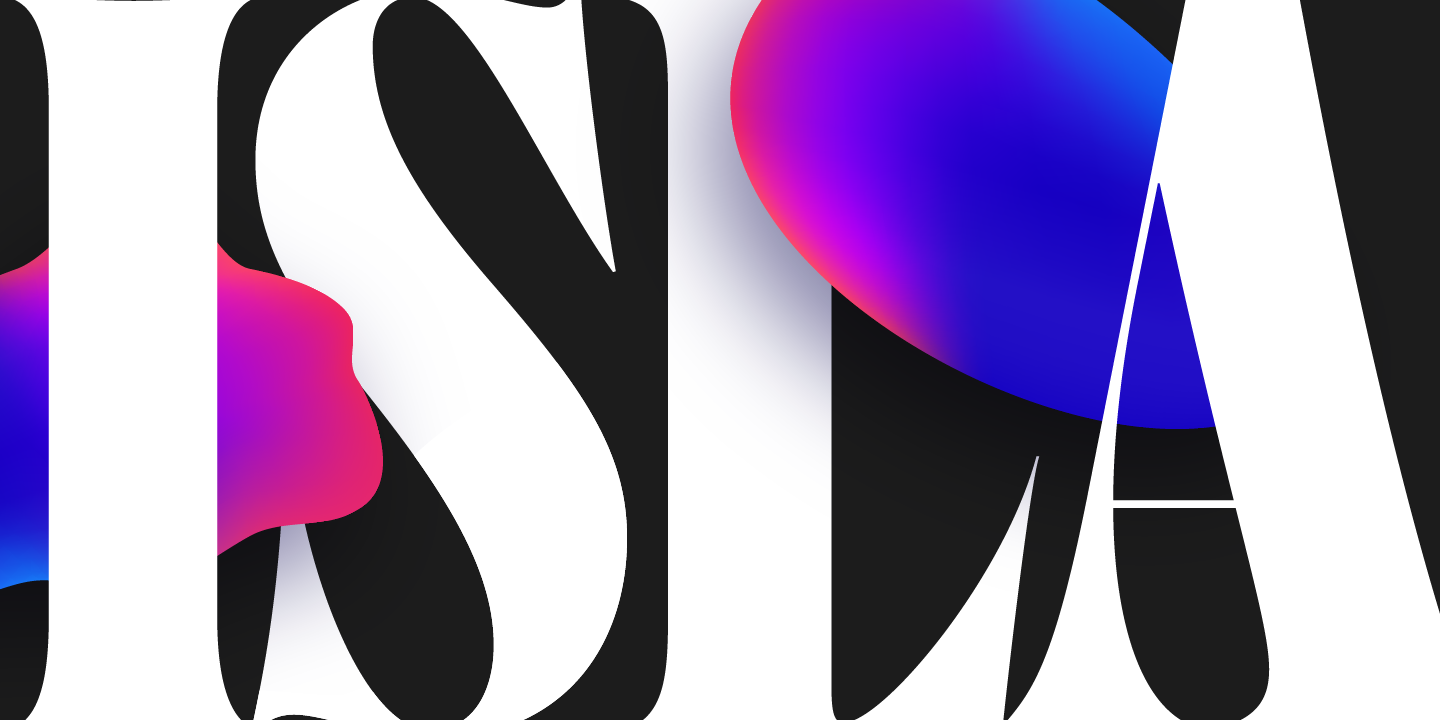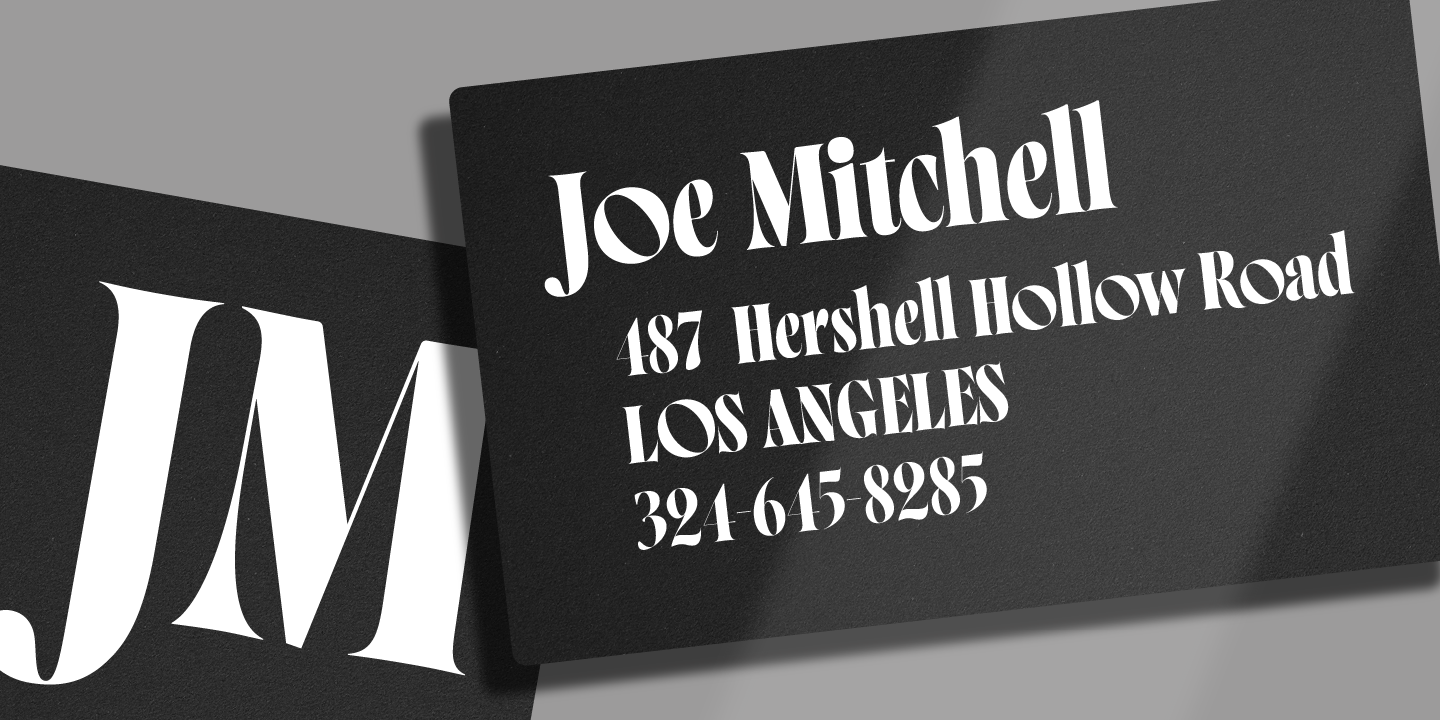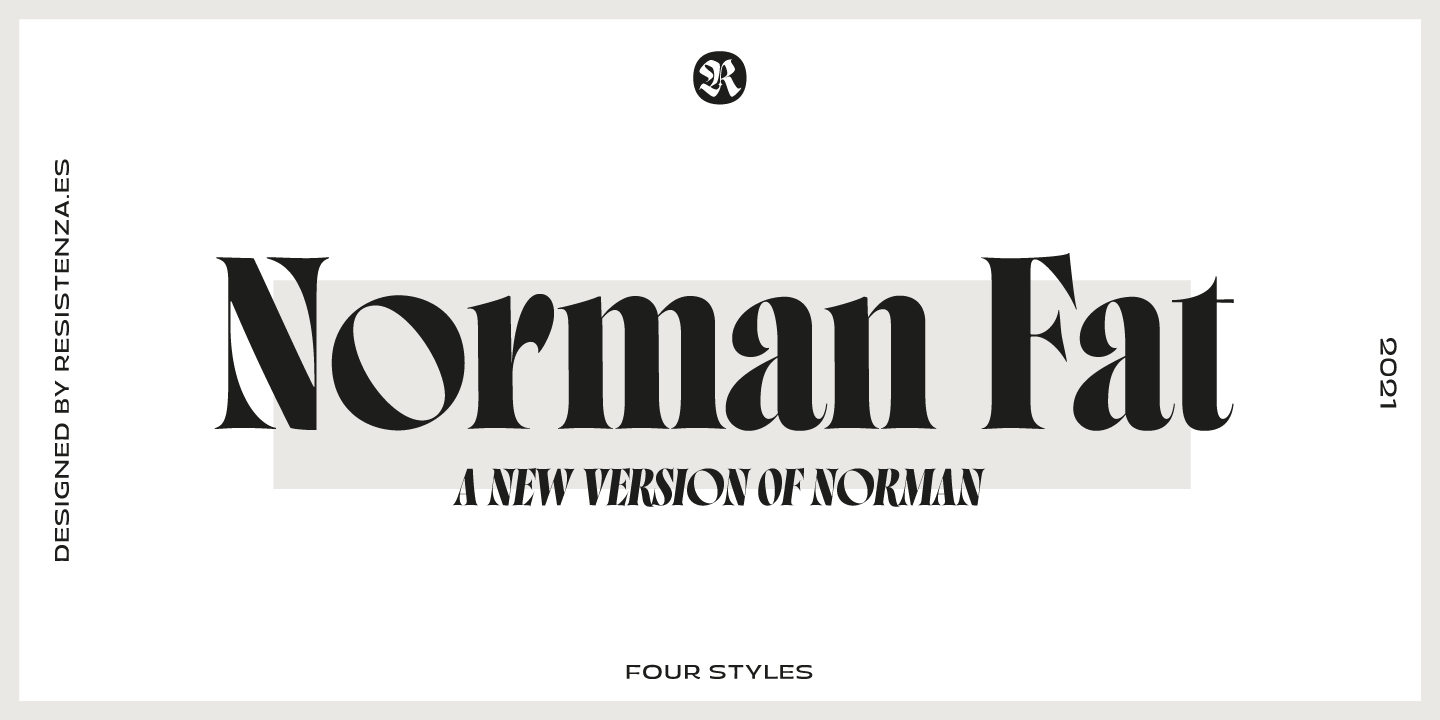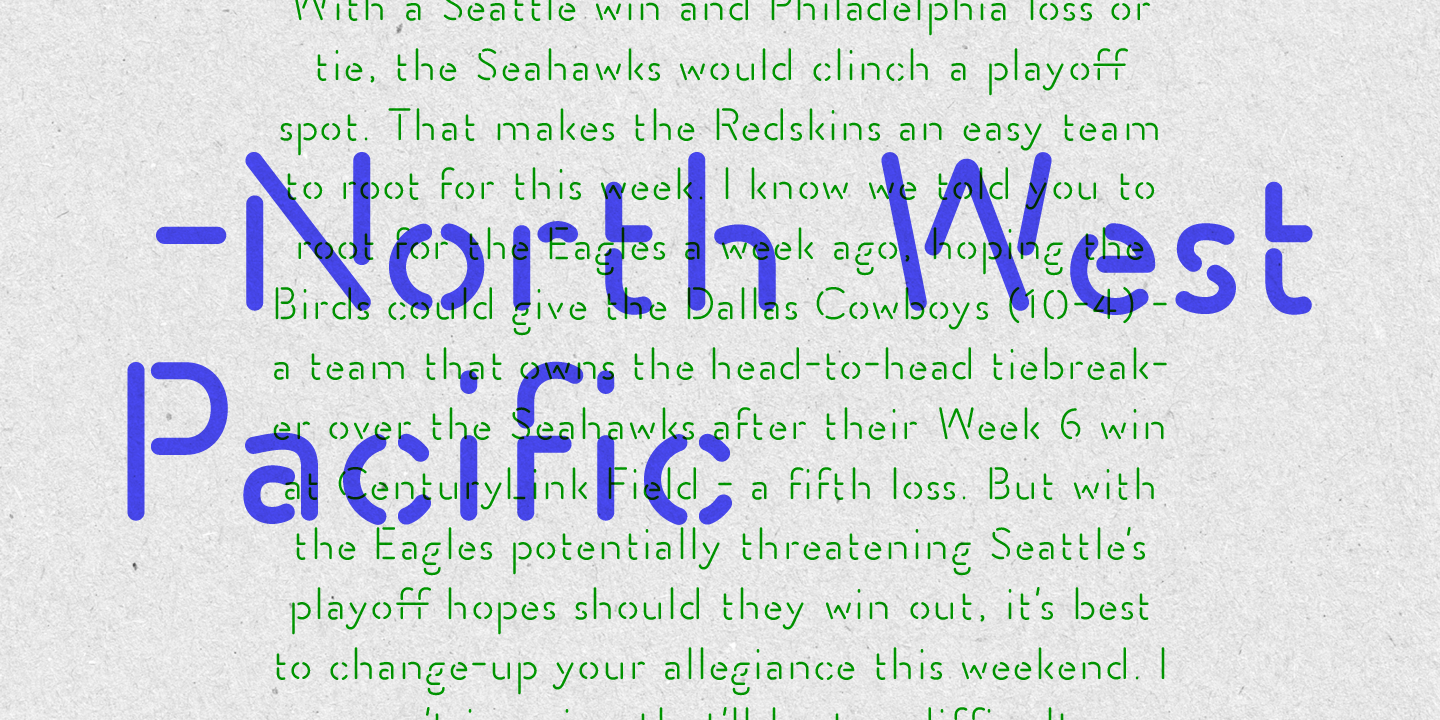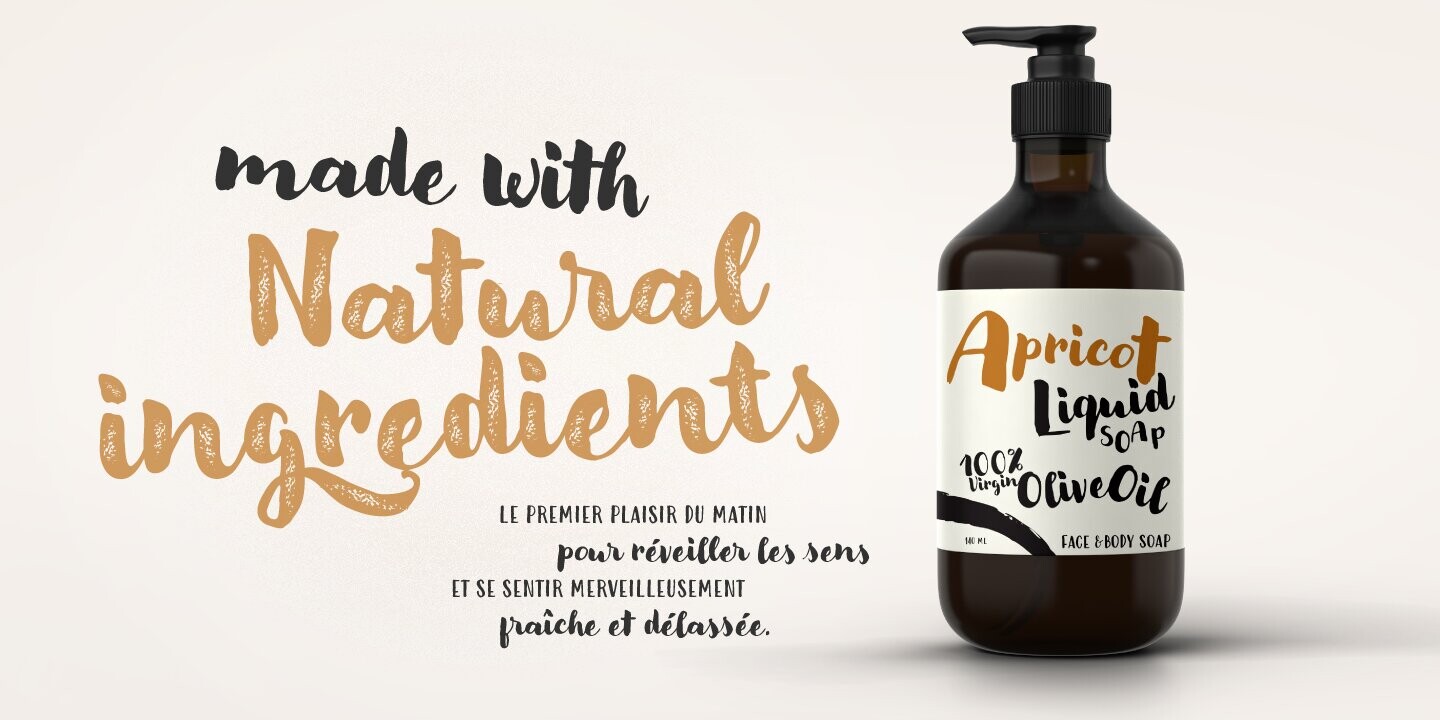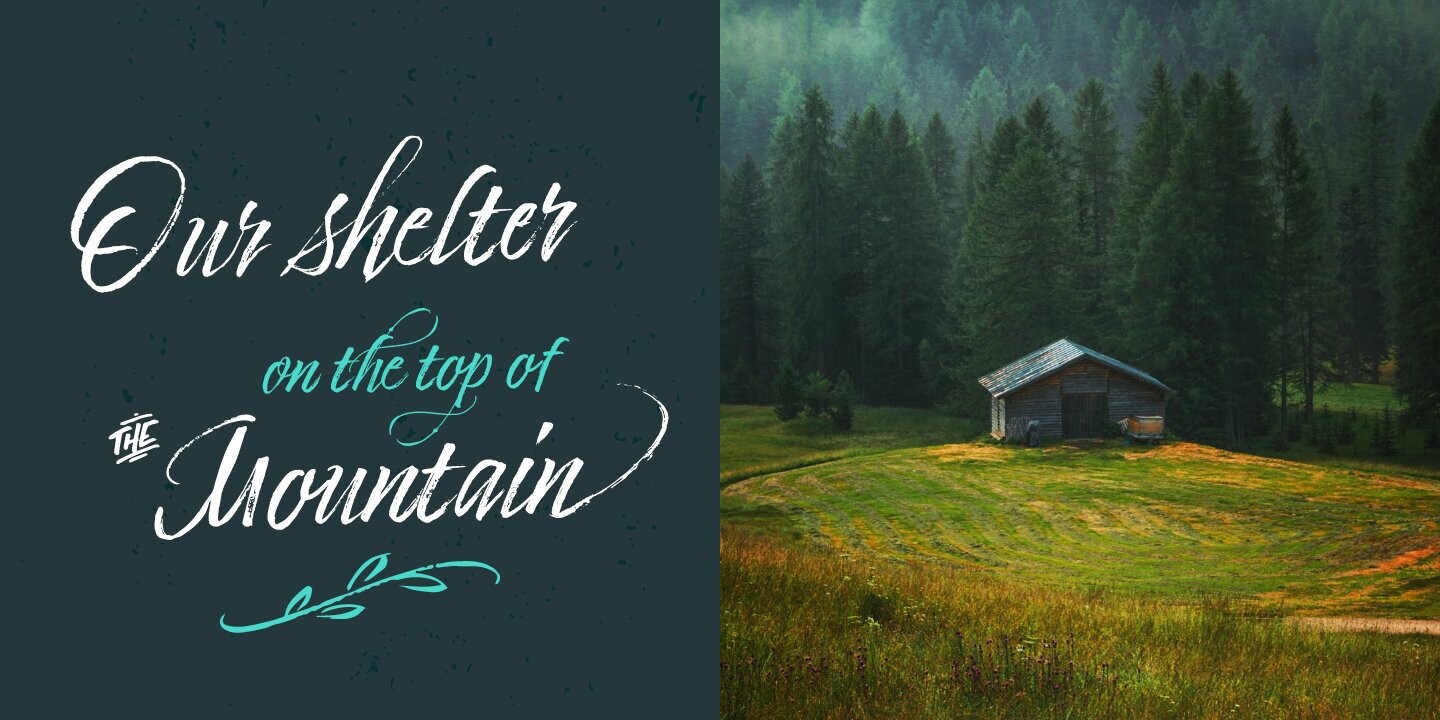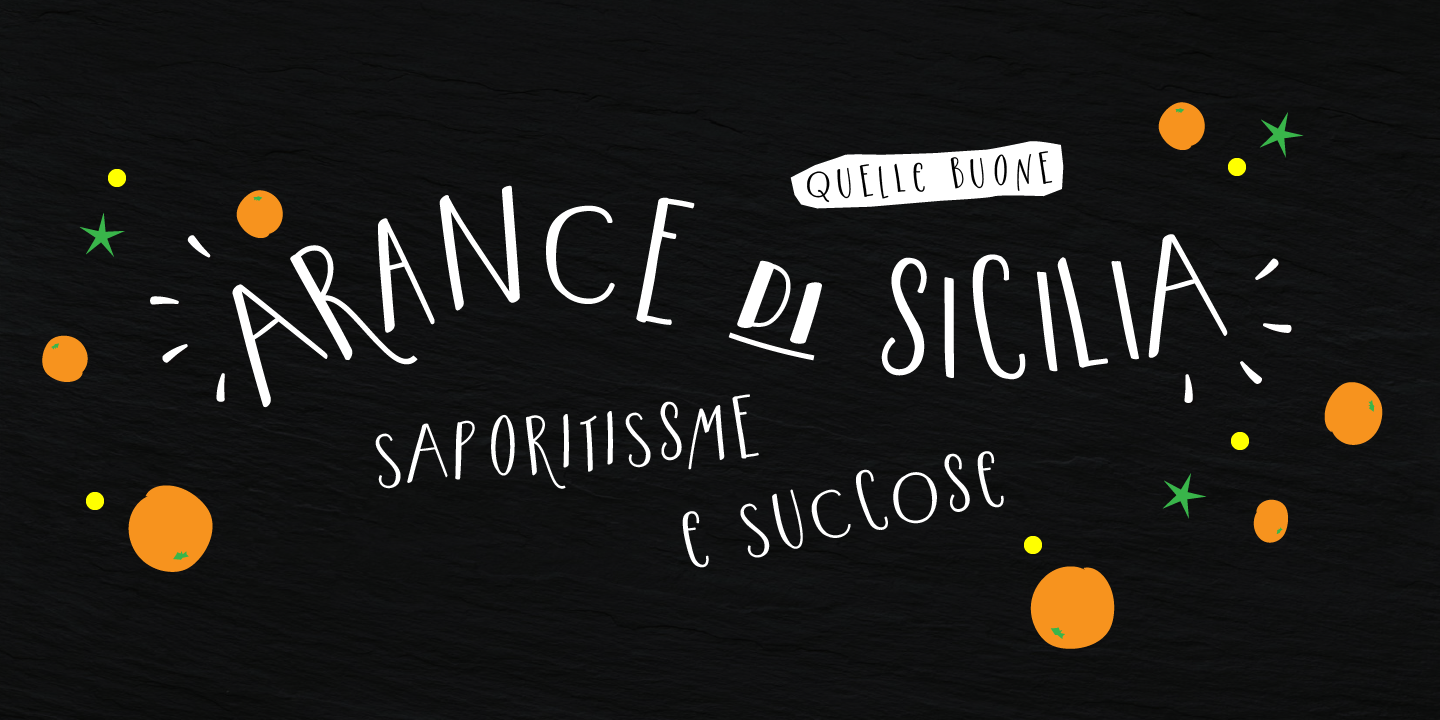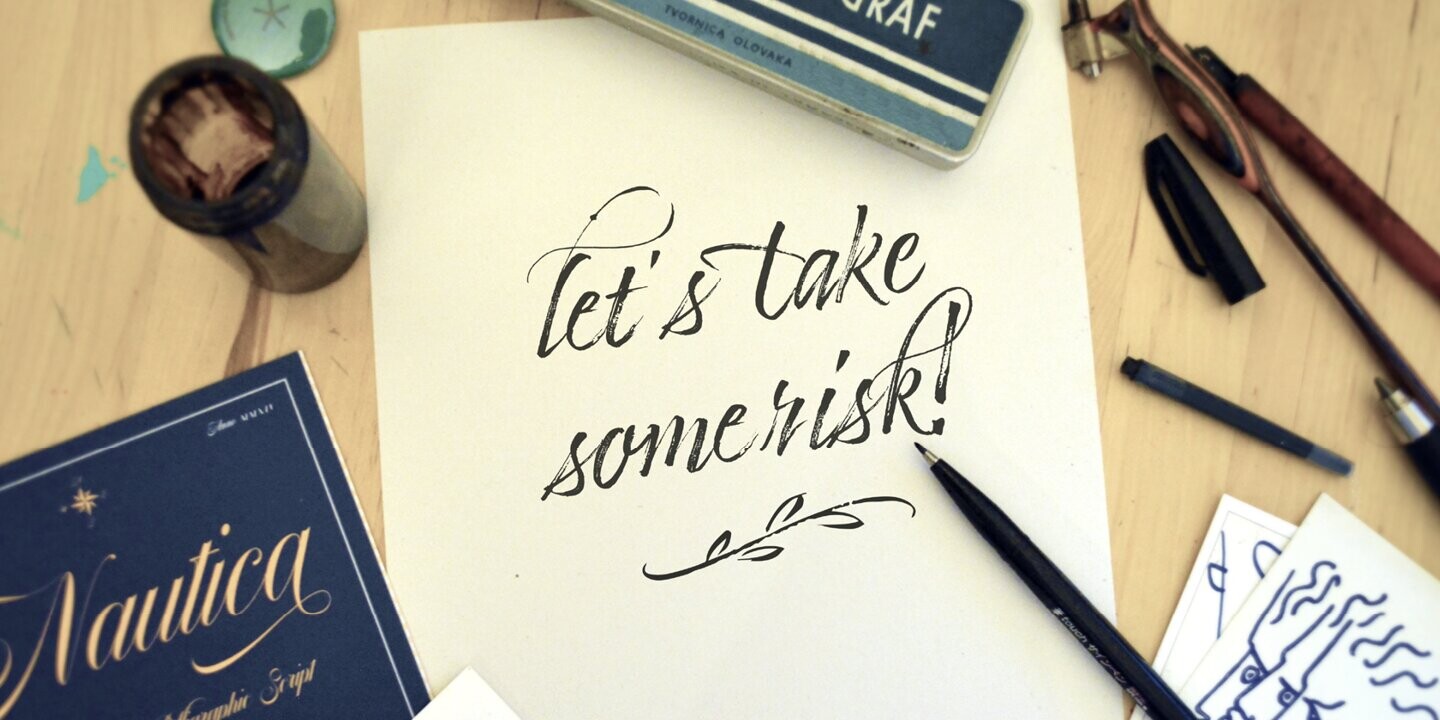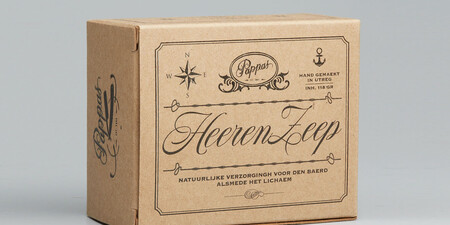
Fonts von Resistenza
Resistenza ist die erste italienisch-spanische Art Foundry mit Sitz in Valencia, Spanien und Turin, Italien, gegründet 2008 mit über 100 Font Familien. Spezialisiert auf kalligrafische, Display- und handgeschriebene Fonts.
Resistenza ist spezialisiert auf Schriftdesign, Branding, Kalligrafie und Lettering. Giuseppe Salerno und Paco González sind die beiden Gründer, Italiener und Spanier, die ihre Leidenschaft für das Schreiben und die handgefertigten Buchstaben zu ihren Stärken gemacht haben. Pinselartige Schriften, kalligrafische Striche, Originalität in den Gesichtern sind ihr bestes Merkmal. Die erste Schrift war Afrobeat, eine mehrzeilige Rundschrift, die sich sehr schnell entwickelte und ihr erstes Produkt auf der Liste wurde. Aber danach gab es viele andere Experimente und ausdrucksstärkere Designs wie die Berliner Fraktur oder eine englische Kupferschrift wie Copperlove, die Giuseppe Salernos Hand in eine Schrift bringt.
Mitbegründer
Paco Gonzalez
Paco González ist ein spanischer Grafikdesigner aus Valencia. Sein Hintergrund reicht von der Arbeit in der Reisebranche und im Marketing bis hin zum Grafikdesign. Er entwickelt visuelle Identitäten und typografische Projekte. Seine typografische Arbeit konzentriert sich auf handgeschriebene Schriften, Skripte und illustrative Icons, Dingbats und kleine Skizzen.
Mitbegründer
Giuseppe Salerno
Giuseppe Salerno mischt seine kalligrafischen Fähigkeiten mit seinem Wissen über Schriften. Er ist seit 14 Jahren in der Kreativbranche tätig und hat in Berlin, Madrid, Valencia und Seattle für Kunden in aller Welt gearbeitet. Zusammen mit Paco González gründete er das Studio Resistenza.es. Pinselstriche, kalligrafische Striche, Originalität in der Schriften sind ihr wichtigstes Stilmerkmal. Sie erstellen Schriften , um ihre Grafikdesign-Projekte zu verbessern, und sie praktizieren Kalligrafie als Grundmethode für die Schrift Schriften.